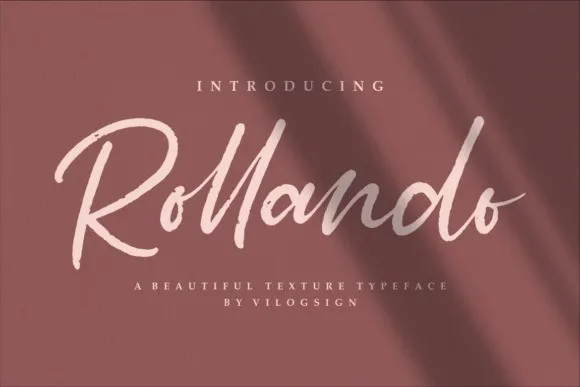
Rollando Script Font – Download Grátis
Este é uma bela tipografia textura, mas também uma fonte script com estilo de escrita de arte. Esta é a introdução do Rollando Font, criado e compartilhado pelo Vilogsign. Inspirada na tipografia clássica, a Rollando Script traz seu próprio estilo único para qualquer projeto de design. Este incrível conjunto de letras feitas para headlines em todas as escalas, bem como textos que variam tanto para o máximo quanto para o mínimo. Seja para web, impressão, imagens em movimento ou qualquer coisa mais – o Rollando sempre será um espetáculo ao olhar.